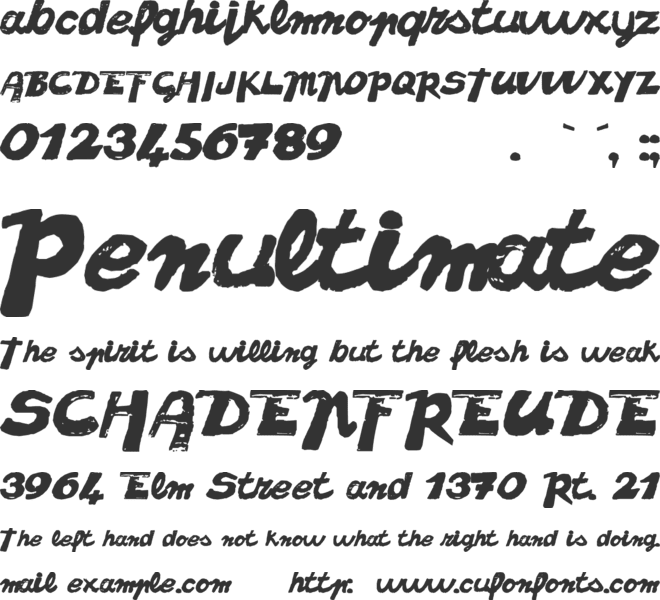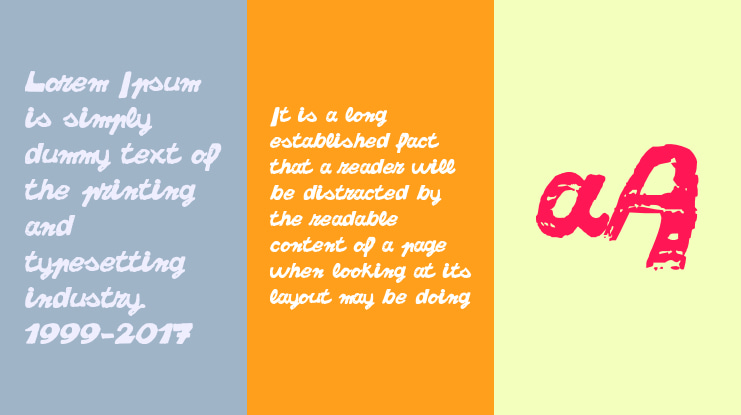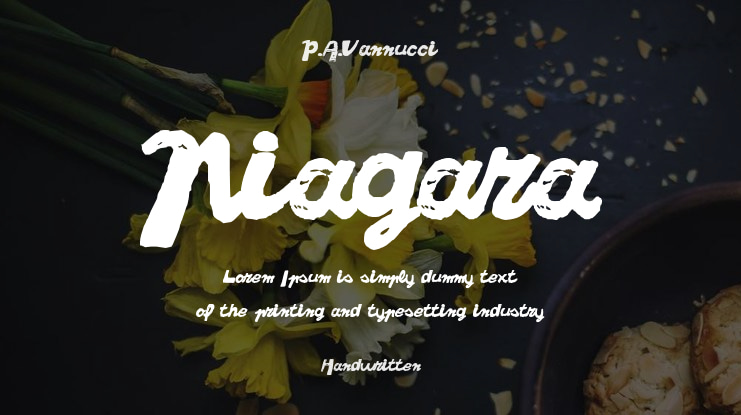
Niagara Font
P.A.Vannucci
NIAGARA font: direttamente dal film diretto da Henry Hathaway e interpretato da Marilyn Monroe, il font inedito per tutti gli estimatori del film. Da notare il ritocco necessario in Photoshop per conferire, alla titolazione, l'originale bordatura.
NIAGARA font: directly from the Best movie by Henry Hathaway, with Marilyn Monroe, the original font for all lovers. Use ADOBE Photoshop for the original border from title.